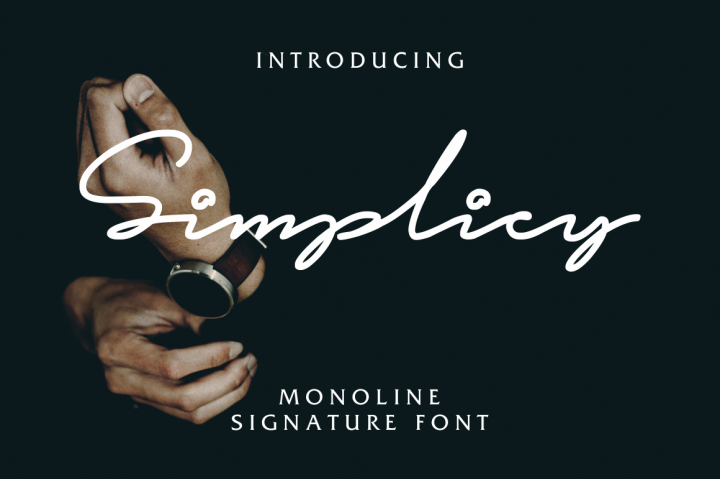
Simplicy Signature Font – Download Grátis
A fonte ‘Simplicy Signature Font’ é uma escolha perfeita para os mais criativos que procuram um estilo natural e profissional. Ela foi criada com mão, oferecendo uma aparência handwritten autêntica e elegante. Esta font se destaca por sua versatilidade, sendo ideal tanto para a criação de logotipos quanto para design de revistas, cartões de visita, embalagens ou até mesmo roupas customizadas. Suas linhas leves e sutis garantem um toque sofisticado em qualquer projeto que ela seja usada. Os estilistas buscam sempre algo que destaque sua marca no mercado fashionista; a simplicidade da ‘Simplicy Signature Font’ é perfeita para essa necessidade, oferecendo uma fórmula de sucesso para qualquer projeto visual que exija um estilo autêntico e elegante. Sem dúvida, ela será uma ferramenta indispensável para designers atentos ao detalhe em todas as suas criações.